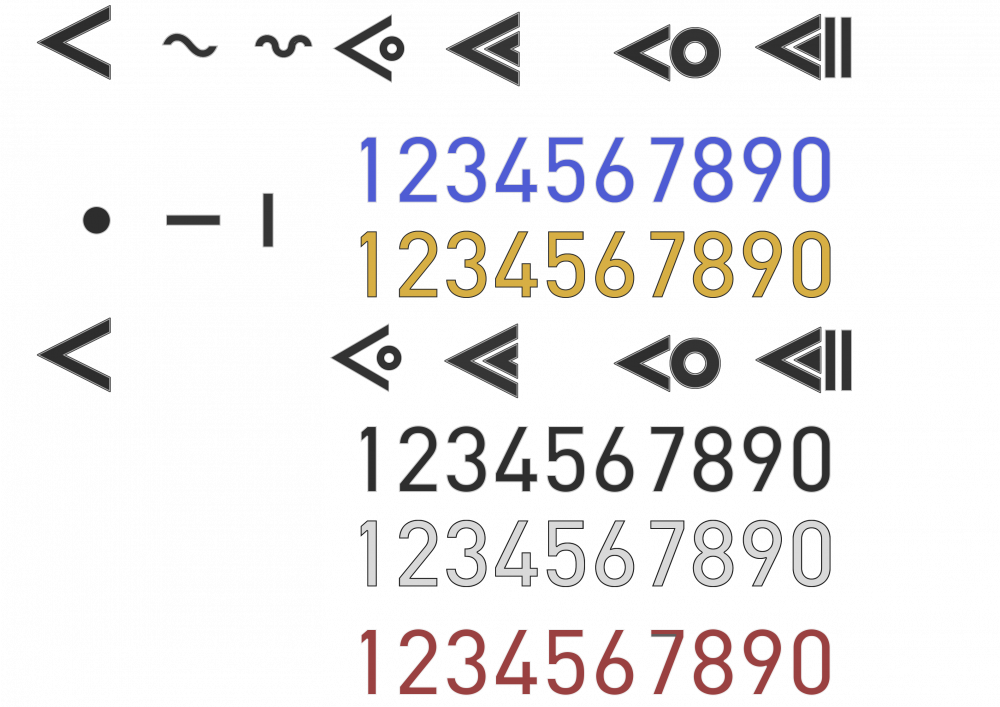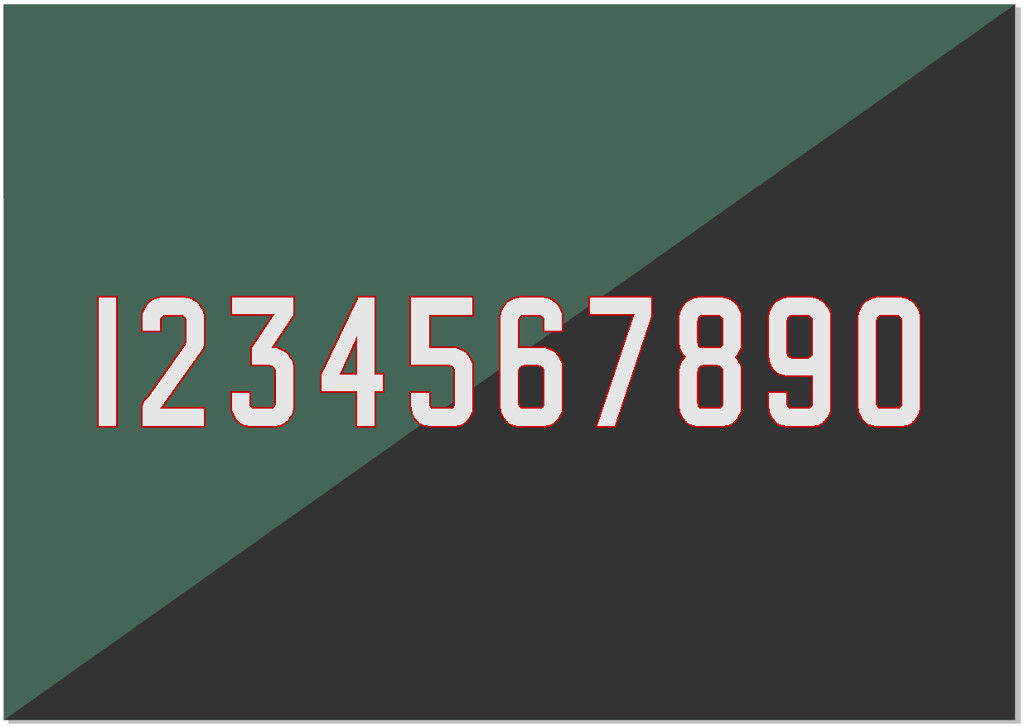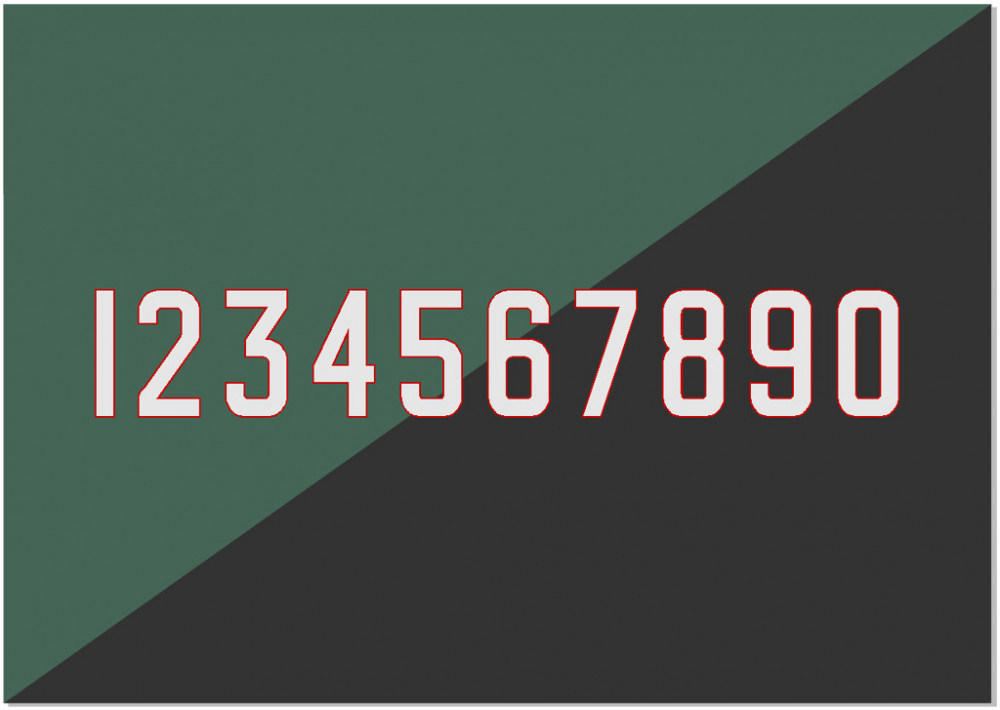
Гость deleted@171995 Опубликовано: 23 сентября 2018 А ни у кого нет цифр, шрифтов для скинов? У меня со старичка осталось кое-что, но тогда размеры были не очень большие (1024*1024), поэтому в новом Ил-2 они смотрятся не очень хорошо. Шрифты для немцев и англосаксов у меня есть. Под советов сейчас ничего нет. В пристёжке прикрепил образец того чего ищу.
[I.B.]ViRUS Опубликовано: 23 сентября 2018 "таймс нью романом" малевали... Цифры рисовать нужно ручками, выглядят при этом естественней. Какого-либо чёткого стандарта не было; в случае с лавками - скорее исключение, чем правило.
Гость deleted@171995 Опубликовано: 23 сентября 2018 59 минут назад, [I.B.]ViRUS сказал: "таймс нью романом" малевали... Цифры рисовать нужно ручками, выглядят при этом естественней. Какого-либо чёткого стандарта не было; в случае с лавками - скорее исключение, чем правило. тайм нюьс совершенно некрасиво. у меня есть шрифты специализированные (немцы, англосаксы), а на наших нету. симмперспайнтшоп помер оказывается. вот не знаю где взять, например, цифры на Ла в высоком качестве.
[I.B.]ViRUS Опубликовано: 23 сентября 2018 я это всё к чему вёл - не используйте шрифты на скинах от слова вообще. Буквы и цифры нужно рисовать вручную.
Гость deleted@171995 Опубликовано: 23 сентября 2018 36 минут назад, [I.B.]ViRUS сказал: я это всё к чему вёл - не используйте шрифты на скинах от слова вообще. Буквы и цифры нужно рисовать вручную. есть стандартные шрифты для немцев. они полностью соответствуют фото. есть шрифты для англосаксов. даже для советов есть шрифт, но на ранние свистки. у тебя есть нарисованные цифры в высоком разрешении? поделишься?
[I.B.]ViRUS Опубликовано: 23 сентября 2018 с готическими шрифтами ещё ладно, но у наших кто как в полках номера рисовал, не до шаблонов было как-то, да и в отечественной авиации выпендрёжничество не так развито, как у тех же немцев или союзников. А трафареты введены были уже после войны. Поэтому и следует рисовать цифры и буквы вручную, выглядеть это будет лучше, чем чёткие, одинаковые буквы.
Гость deleted@171995 Опубликовано: 23 сентября 2018 Только что, [I.B.]ViRUS сказал: с готическими шрифтами ещё ладно, но у наших кто как в полках номера рисовал, не до шаблонов было как-то, да и в отечественной авиации выпендрёжничество не так развито, как у тех же немцев или союзников. А трафареты введены были уже после войны. Поэтому и следует рисовать цифры и буквы вручную, выглядеть это будет лучше, чем чёткие, одинаковые буквы. это было на начальном периоде войны в ввс ркка. но ведь уже после сталинграда номера наносили стандартные. вот выше рисунок есть. мне бы их в высоком качестве.
=2ndSS=temkatt Опубликовано: 23 сентября 2018 Если нужны непременно шрифты - то только ручками самому создавать. Есть программка например High-Logic FontCreator (платная). В ней можно нарисовать самому себе любой шрифт. Я например делал по такой схеме: искал фото с образцами номеров, потом в фотошоп вырезал и переводил в .png, затем импорт из картинки в High-Logic FontCreator, ну а там уже ручками правил до достижения приемлемого для меня результата. Для нашего сквада было требование - бортовые должны читаться с больших расстояний, поэтому цифры чёткие, плюс в случае пополнения новые бортовые проще шрифтом рисовать. Для себя основное требование ставил - номера должны соответствовать эпохе. Но если преследовать целью историческую достоверность, то камрад [I.B.]ViRUS прав - рисовать только ручками, плюс ещё с кистями играться в фотошопе. 3
Гость deleted@171995 Опубликовано: 23 сентября 2018 6 часов назад, =2ndSS=temkatt сказал: Если нужны непременно шрифты - то только ручками самому создавать. Есть программка например High-Logic FontCreator (платная). В ней можно нарисовать самому себе любой шрифт. Я например делал по такой схеме: искал фото с образцами номеров, потом в фотошоп вырезал и переводил в .png, затем импорт из картинки в High-Logic FontCreator, ну а там уже ручками правил до достижения приемлемого для меня результата. Для нашего сквада было требование - бортовые должны читаться с больших расстояний, поэтому цифры чёткие, плюс в случае пополнения новые бортовые проще шрифтом рисовать. Для себя основное требование ставил - номера должны соответствовать эпохе. Но если преследовать целью историческую достоверность, то камрад [I.B.]ViRUS прав - рисовать только ручками, плюс ещё с кистями играться в фотошопе. Да это понятно. Я по фото делал раньше. Я спрашивал же цифры, например, на Ла, но в высоком разрешении. От старичка у меня есть. Но на новых скинах они выглядят не очень. Раньше было 1024*1024 пикс., а сейчас разрешение гораздо выше.
KOHTYP Опубликовано: 23 сентября 2018 Нет шаблонов цифр для советских самолётов времён великой отечественной войны. Разглядывая старые фотографии самолетов, вглядываясь в цифры, понимаешь, что в каждой эскадрилье были свои обозначения и шрифты различия для узнаваемости в воздушном бою. Поэтому, выбирайте похожий шрифт из того, что есть и дорисовывайте, обрезайте, подтирайте, подгоняйте под истину и не нойте, что не можете найти шаблон. Проявляйте фантазию и смекалку, чувствуйте себя художником а не маляром и у вас всё получится.
Гость deleted@171995 Опубликовано: 23 сентября 2018 41 минуту назад, KOHTYP сказал: Нет шаблонов цифр для советских самолётов времён великой отечественной войны. Разглядывая старые фотографии самолетов, вглядываясь в цифры, понимаешь, что в каждой эскадрилье были свои обозначения и шрифты различия для узнаваемости в воздушном бою. Поэтому, выбирайте похожий шрифт из того, что есть и дорисовывайте, обрезайте, подтирайте, подгоняйте под истину и не нойте, что не можете найти шаблон. Проявляйте фантазию и смекалку, чувствуйте себя художником а не маляром и у вас всё получится. чего ты огрызаешься? я русским языком выше сказал-что я рисовал цифры. даже надписи рисовал по фото и что? я нормально спросил есть или нет. потому что симмерс помер. к чему твой флуд? нормальным русским языком спросил. нет. надо полить дермьмом окружающих. Шаблоны есть. Хочешь на Як, хочешь на Ла и т.п. Но они в малом разрешении. В этом проблема.
KOHTYP Опубликовано: 23 сентября 2018 Не понимаю, почему ты решил, что я огрызаюсь и поливаю дерьмом? Только по тому, что предлагаю рисовать самому? Флуд? Ты нормально спросил, есть или нет, я нормально ответил, что нет и объяснил почему. Если тебе не нравится ответ, это не является агрессией против тебя. Не удивлюсь, что дальше пойдёт флуд. Считаю для себя тему закрытой и не интересной.
-OSF-Joe Опубликовано: 14 мая 2019 7 часов назад, deSAD сказал: "Я так вижу", и весь сказ ? Неправильная картинка, да. Такая должна быть! 1